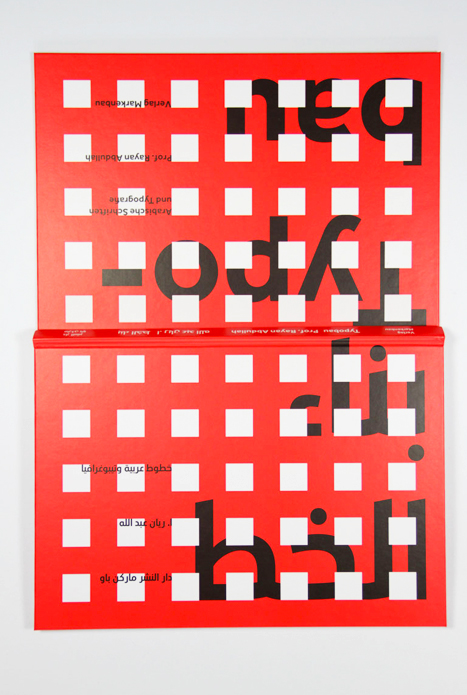
Typobau – Arabische Schriften und Typografie
Typobau –Arabische Schriften und Typografie ist neu erschienen und herausgebracht vom Verlag Markenbau. Professor Rayan Abdullah beschäftigt sich in dieser Publikation als einer der ersten mit dem Thema arabische Schrift und Typografie. Zugehörig zu dem Buch gab es auch eine Ausstellung. Professor Abdullah nutzte seine Ausstellung, um unter anderem jungen arabischstämmigen Berlinern Mut zu machen, sich auf Ziele, auf Qualitätsbewusstsein, auf Kreativität einzulassen.
Arabische Schrift und Kalligrafie gehören unmittelbar zusammen. Frühere Kalligrafen kreierten die schönsten arabischen Schriften. Mit dem sich schnell ändernden Zeitgeist haben sich die Anforderungen an die arabische Schrift allerdings geändert beziehungsweise neu definiert. Das Buch zeigt darüber hinaus arabische Logos für deutschebeziehungsweise weltweite Unternehmen, die er gestaltet hat.
Das vorliegende Buch Typobau repräsentiert die aktuell besten arabischen Schriften, die in Leipzig und Berlin in Zusammenarbeit mit dem Büro Dalton Maag in London entstanden sind.
Es werden die Schriften McDonalds Arabic, Transport Dubai Arabic, Cordale Arabic, Ubuntu Arabic, Barclaycard Co Arabic, Aktiv Grotesk Arabic und die gesamte Schriftfamilie der arabischen Nokia vorgestellt. Rayan Abdullah präsentiert nicht nur seine arabischen Schriften, sondern auch seine arabische Typografie und den Umgang mit ihr.
Typobau –Arabische Schriften und Typografie
Gestaltung: Prof. Rayan Abdullah
Herausgeber: Prof. Rayan Abdullah
Verlag: Verlag Markenbau
Besonderheiten: Die Seitenzahlen beginnen rückwärts, als Tribut an die arabische  Schreibweise. Das Buch öffnet sich wie ein Laptop und wird in diesem Format gelesen.Es gibt einen aufwändigen Schutzumschlag, der gleichzeitig als Plakat genutzt werden kann.